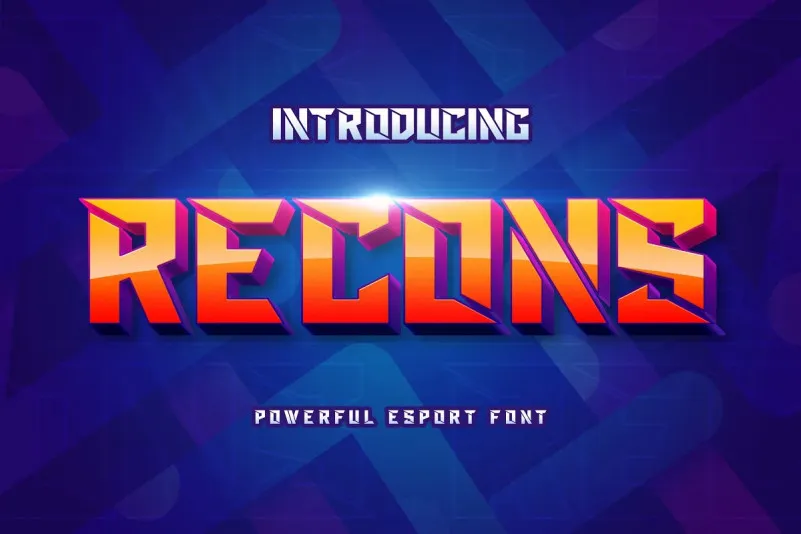
Esta é uma gama moderna e casual de tipos de exibição criada pela Almarkha Type inspirada no título de um cartaz esportivo. Inspirados nessa origem, criamos Recons Font com nuances fortes e desafiadoras, adequadas para o título, tipografia, roupas, outdoors, revistas, catálogos, embalagens, websites e muito mais para as necessidades de design. Ideal para tornar seus designs mais modernos e profissionais. Este pacote de exibição inclui um conjunto sofisticado que certamente enriquecerá a sua identidade visual, mantendo-se fiel à natureza desportiva sem perder o estilismo atual. Em suma, Recons Font é uma opção ideal para designers que desejam dar vida aos seus projetos de design com um acabamento moderno e imprimível na prática.